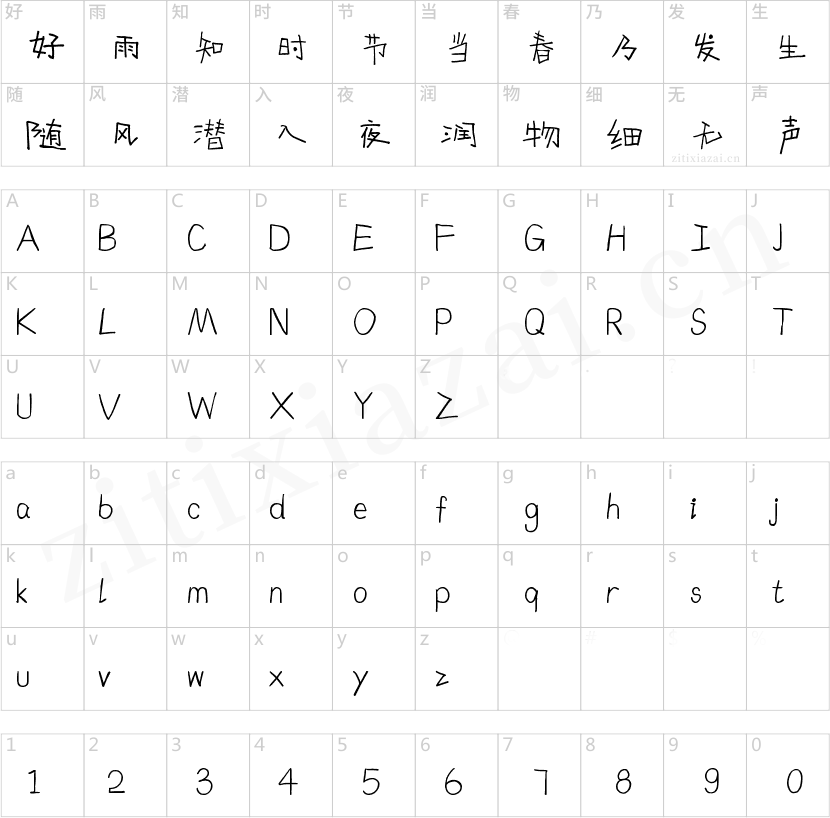
字魂118号-淘气趣味体
字魂字体字小魂淘气趣味体字体是由字魂创意字库设计并生产的一款可商用的字体,被收录于字小魂系列。该字体支持GB-2312标准,包含9169个中文、字母、符号和数字,字体类型偏向硬笔手写,具有活泼、动漫、可爱、简约、时尚、圆润的风格,在市面上广泛用于排版阅读、运动户外、电商等场景。